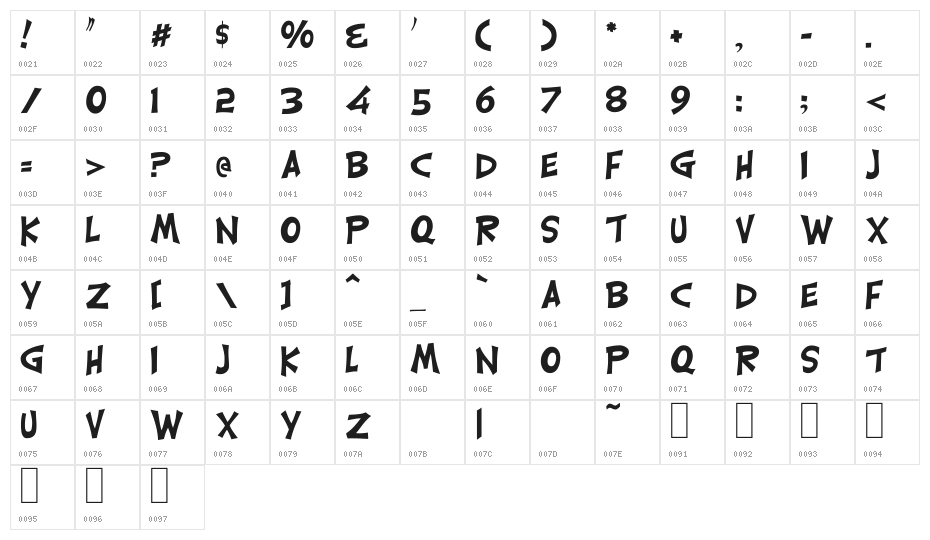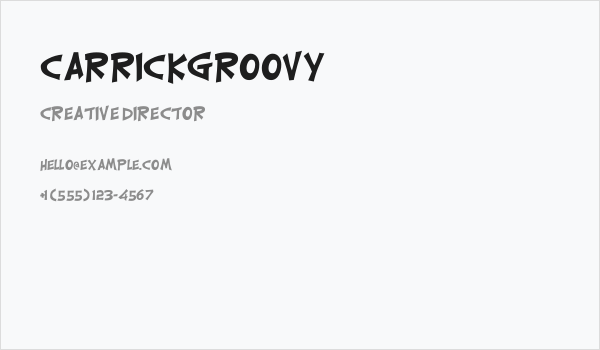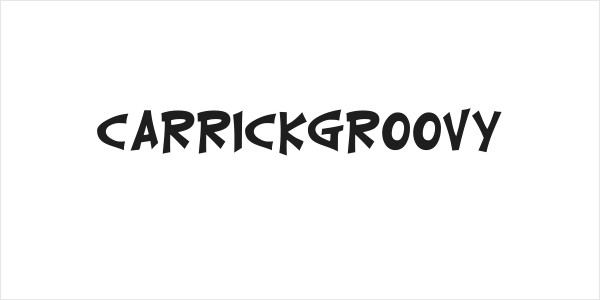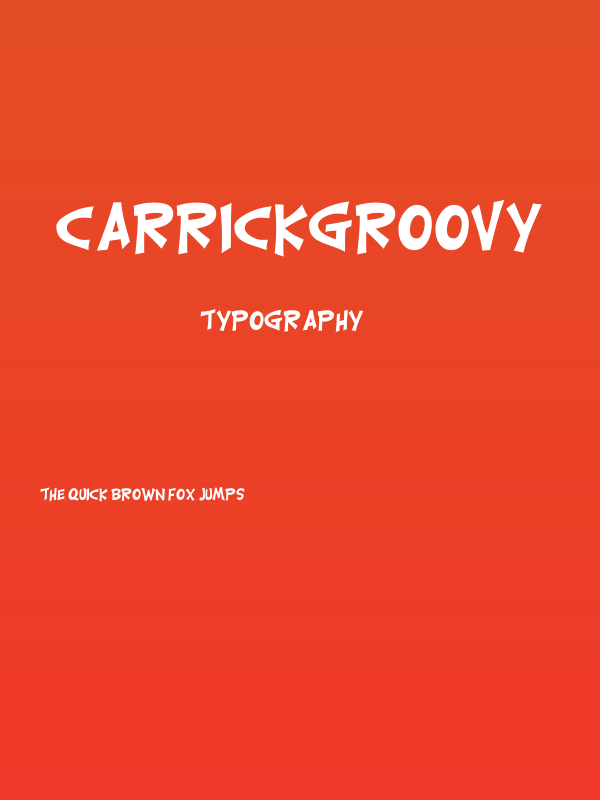
CarrickGroovy Font
| Gesamtstil | Retro, Modern, Playful |
| Vorgeschlagene Projekte | Ideal for posters, album covers, children's books, and any project requiring a fun, eye-catching typeface. |